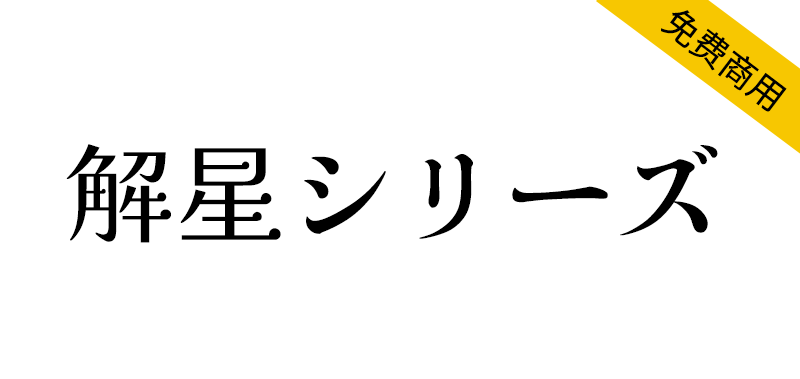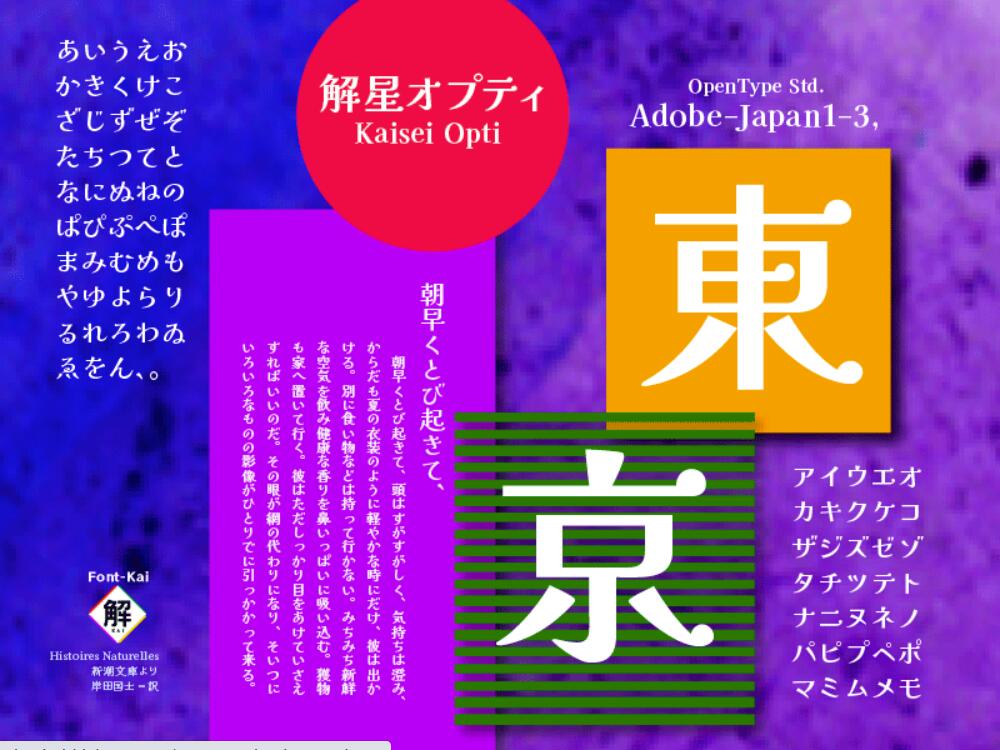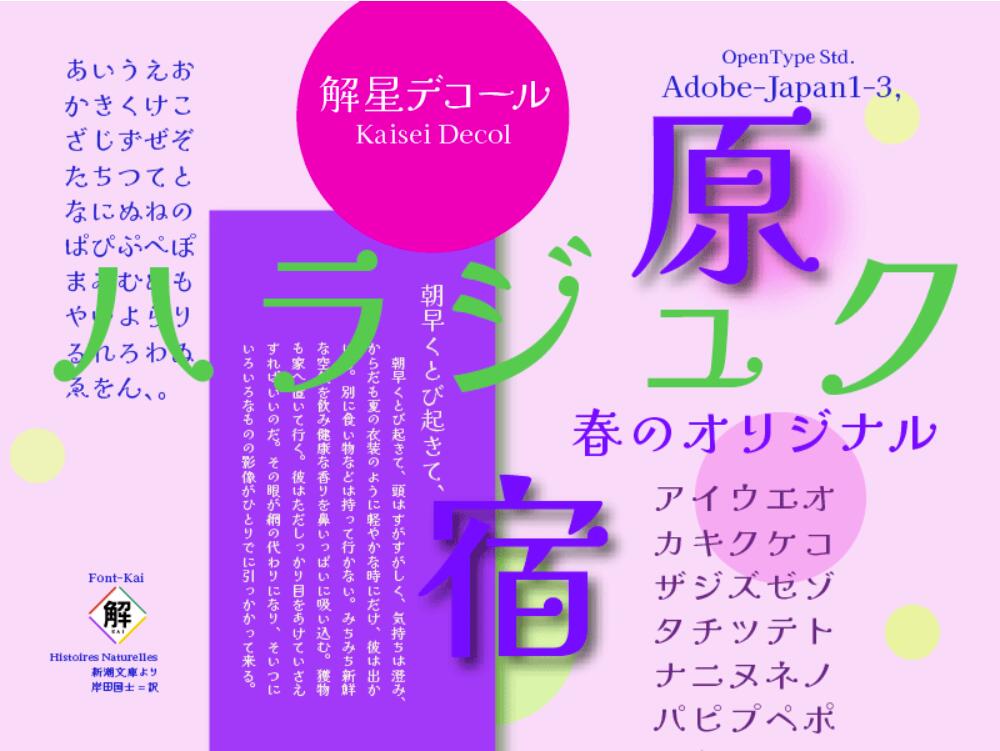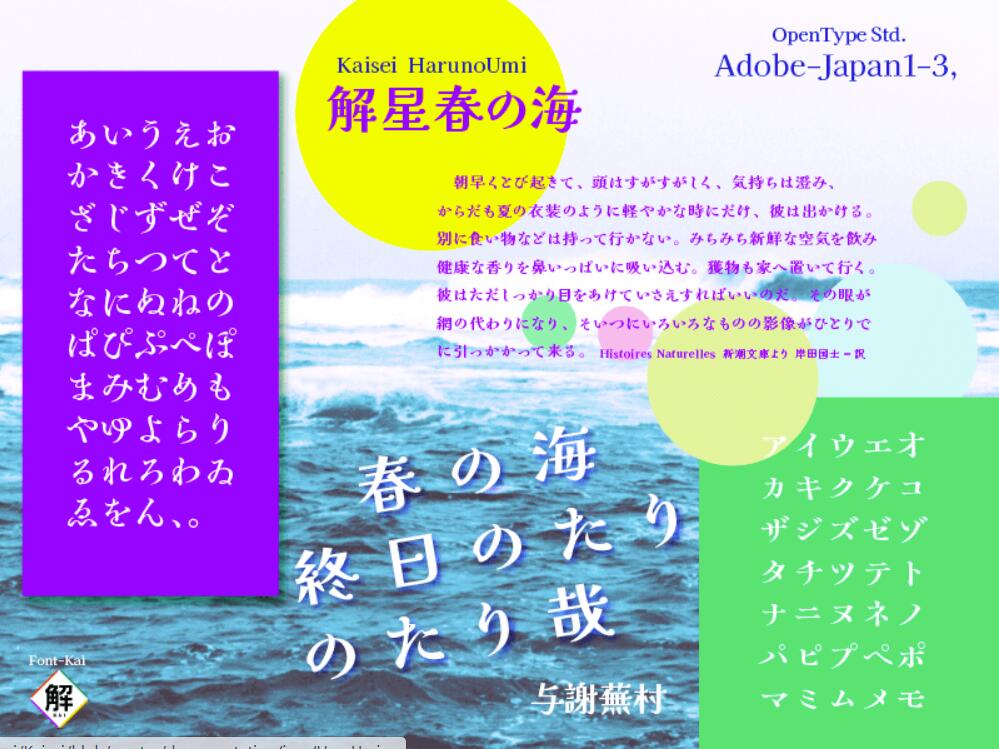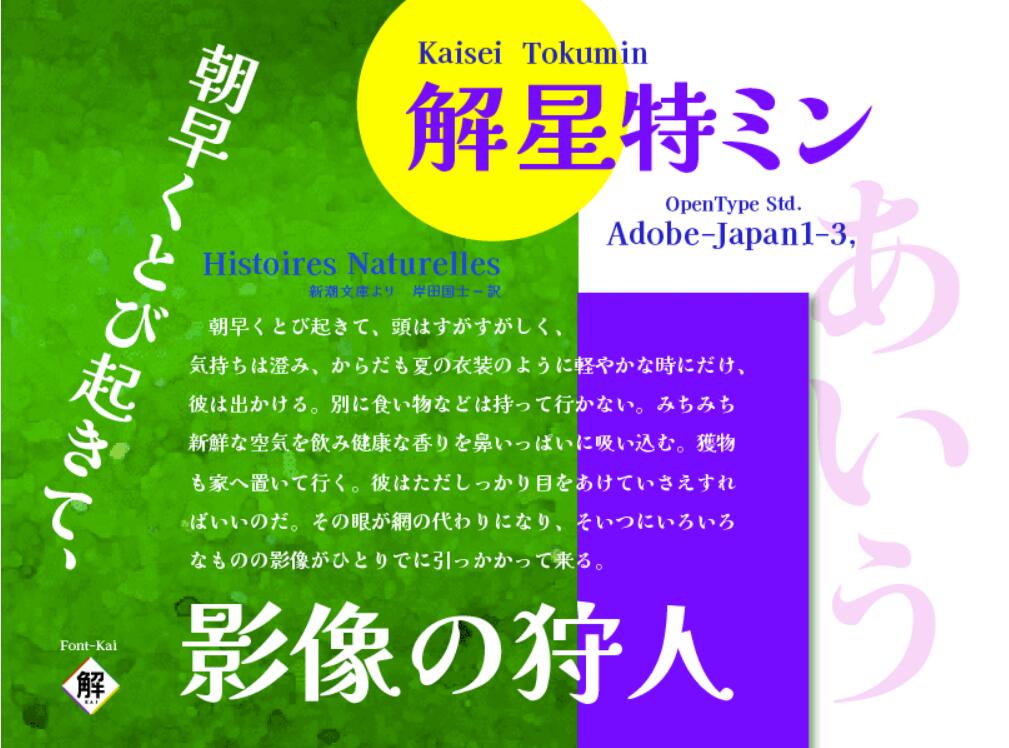
日语字体,一般根据毛笔楷书的书法解释支撑了根基。日语字体是汉字(1画~20画~30画线・・)和平假名・片假名・欧文・记号类,非常字画构成有浓度幅度的字形集合。你必须在视觉上调整这些浓度。网络社会近年来横排表记变多,另外,也成为与其他语言混植的多重字形集合。我的主题是,寻找一条贯穿日语组版蜘蛛网状隧道的光明之路。
“解星项目”于2016年开始制作。根据以往的书法的线构成,采用几何形态的合成来寻找视认性。离开被长期磨砺的毛笔书法会变得不稳定。解星以搔痒的运笔为基础,与以往的笔法不同,在右付和哈内配置星=点的同时,弥补了离开偕法的不稳定性,导出了新的构成要素。汉字的横线以前设定为比明朝体粗。这些都是为了提高电子媒体的再现可读性。
日本語書体は、一般に毛筆楷書に依る書法解釈が根幹を支えてきました。 日本語フォントは、漢字(1画〜20画〜30画線・・)と、ひらがな・カタカナ・欧文・記号類、 大変字画構成に濃度幅のある字形集合です。これらの濃度を視覚的に整えなければなりません。 Net社会の近年は横組み表記が多くなり、また、他言語とも混植する多重な字形集合となっています。 私のテーマは、日本語組版の蜘蛛の巣状のトンネルに(美を以て)貫く光りの道を探すことです。
「解星プロジェクト」は、2016年制作をはじめました。従来書法による線構成から、幾何形態のコンポジションを採り入れ視認性を探した。 永く擦り込まれた毛筆書法を離れると不安定になります。解星では引っ掻くような運筆を基に従来の筆法とは異り、右払いやハネに星=ドットを配置しながら偕法から離れる不安定さを補いつつ、新しい構成要素を導き出しました。漢字の横線は従来明朝体より太めの設定になっています。これらは電子媒体の再現に可読性を高めるためです。
解星オプティ(Kaisei Opti):是一种现代字体,我认为清新的排版外观是年轻一代的首选。
解星デコール(Kaisei Decol):假名采用汉字元素=星点的统一设计。因为排版上有很多小点,所以会产生可爱、快乐、和谐的表情。主要用短文的标题发挥效果吧。请好好地分开使用。
解星 春の海(Kaisei HaruUmi):假名融入了摇曳的膨胀,用扭动让你感觉更接近你的生活。稍小的Katata具有旧明朝体排版的外观。
解星 特ミン(Kaisei Tokumin):假名是特太明朝体假名的省略。这个字体的目的是标题用强有力的假名。当粗字体的密度增加时,字母底部出现不平衡,单词失去呼吸。“Kasei Tokumin 是一种厚字体,旨在即使在一群人中也能保持流畅的可读性,并且不会因强烈的吸引力而失去精致。